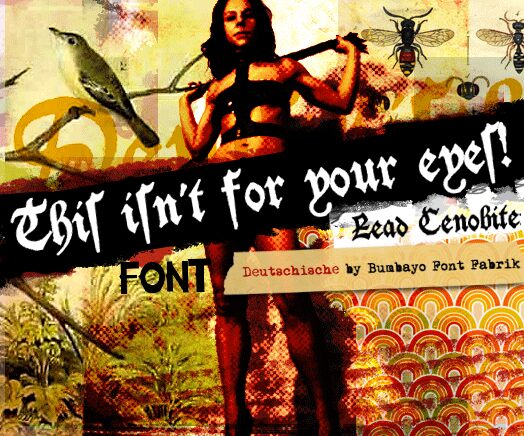
Deutschische von Bumbayo Font Fabrik ist eine kostenlose mittelalterliche Gothic-Schrift mit rauem Blackletter-Charakter. Die Buchstaben orientieren sich am klassischen Fraktur-Rhythmus, mit spitzen Verbindungen, starker vertikaler Ausrichtung und einer handgeschnitzten Optik, die das Schriftbild lebendig hält.
Ideal für Plakate, Bieretiketten, Festival-Grafiken, Buchcover und Musik-Merchandise, wo ein Hauch von Altertum und Schmutz gefragt ist. Als kostenlose Schrift eignet sie sich perfekt für kurze Überschriften, Titelkarten und Monogramme, da die gezackten Striche und großen, geschwungenen Versalien bereits viel Stimmung erzeugen.